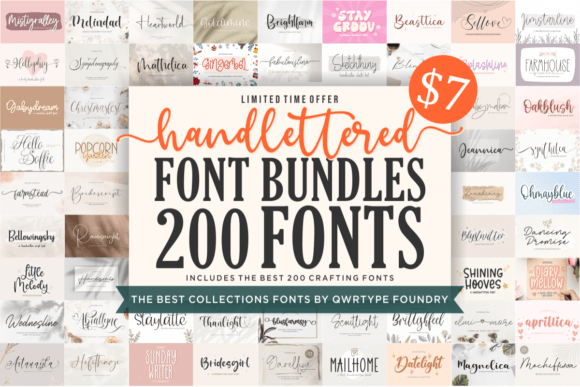
Hand Lettered Font Bundle
Пошук відповідних елементів дизайну може бути складним, але Hand Lettered Font Bundle пропонує виняткову колекцію, яка миттєво покращить вашу роботу.
Незалежно від того, чи створюєте ви продукти POD (друк на вимогу), весільні запрошення або графіку для соціальних мереж, Hand Lettered Font Bundle стане ідеальним вибором.